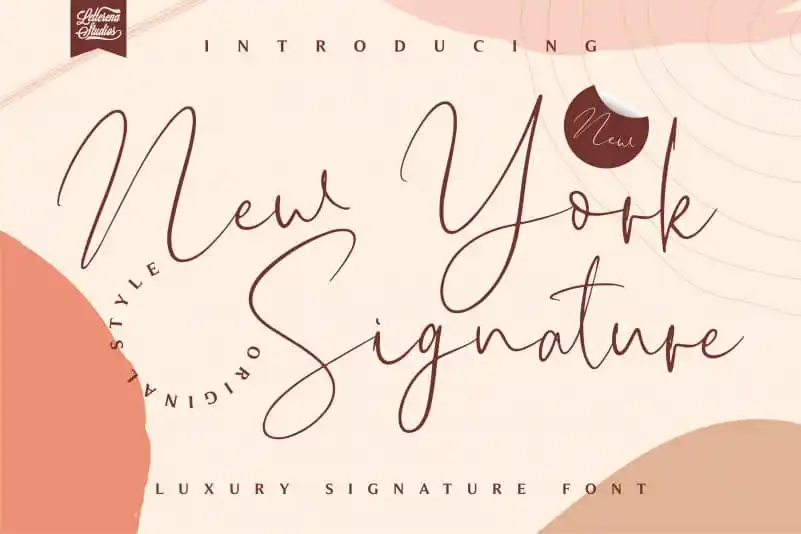
New York Signature Script Font – Download Grátis
Nova York Signature Script Font é uma elegante fonte escrita à mão que se tornará seu próximo querido. Com sua rica e sofisticada aparência, esta fonte pode ser usada de inúmeras maneiras para criar designs únicos e impressionantes. Suavemente romântica, ela traz um toque luxuoso aos seus projetos, dando vida a ideias que você nunca imaginou possuir. Seja para gráficos publicitários ou editoriais, Nova York Signature Script Font será uma escolha definitiva para quem busca um estilo singular e irresistível.